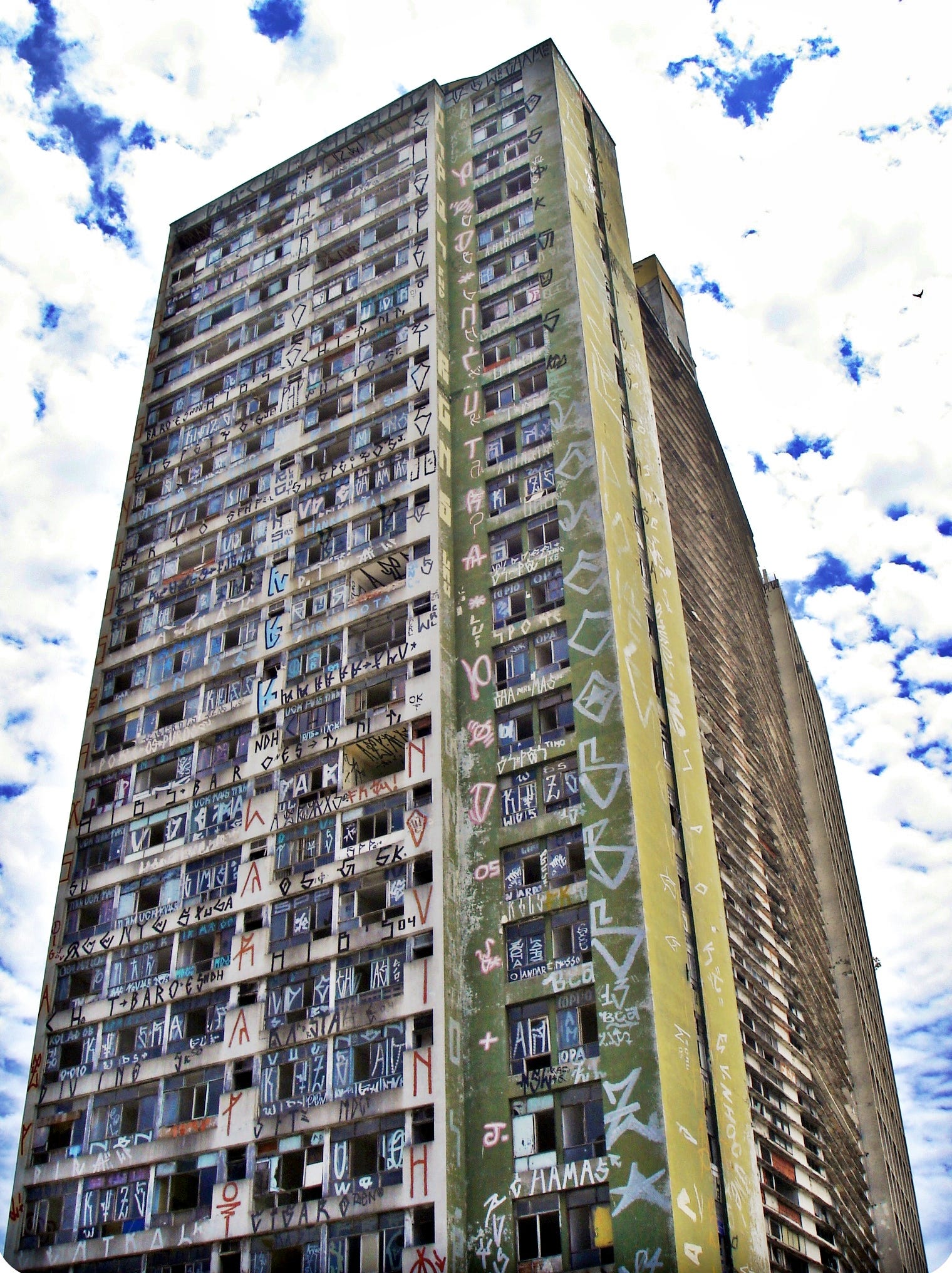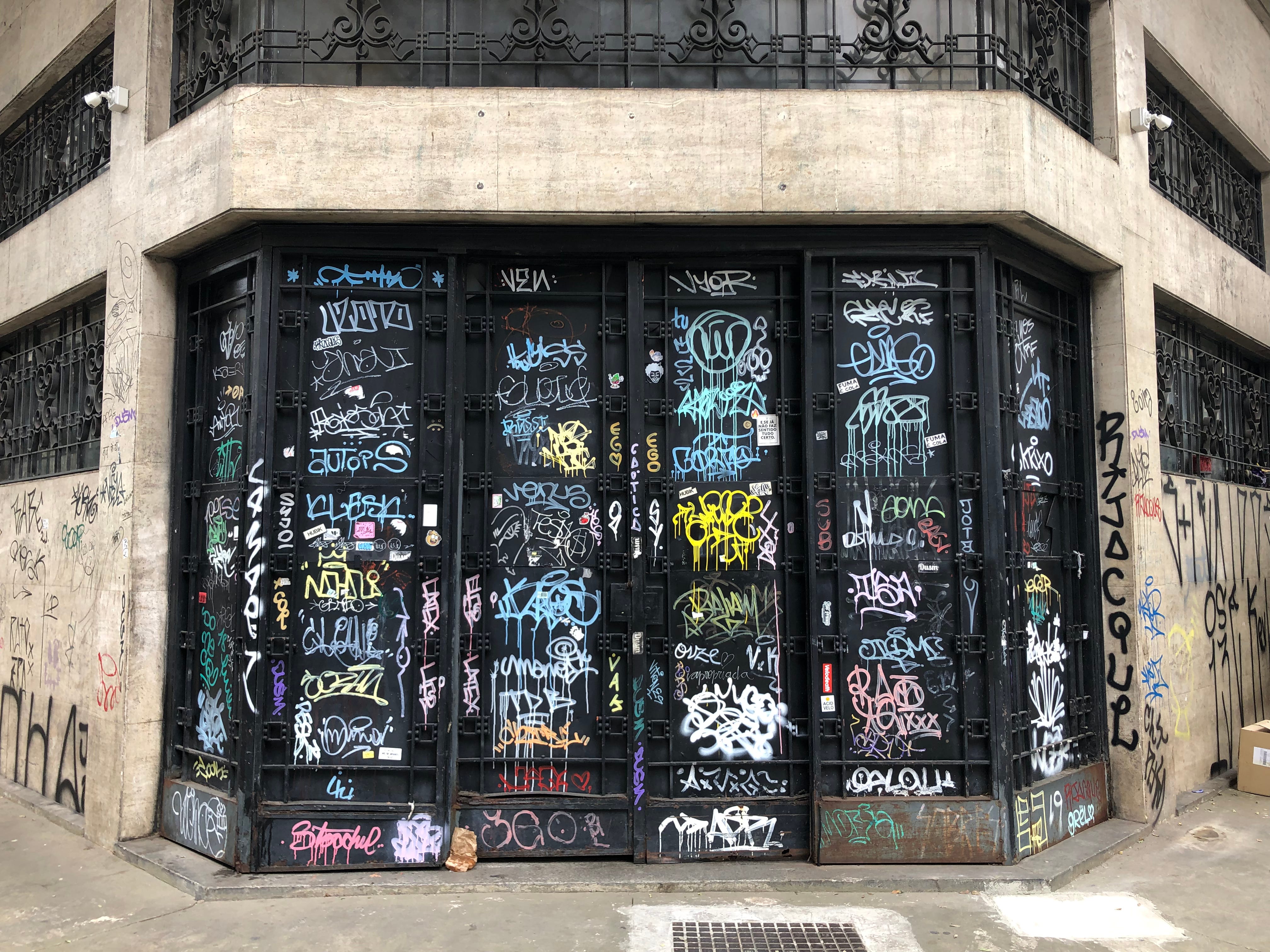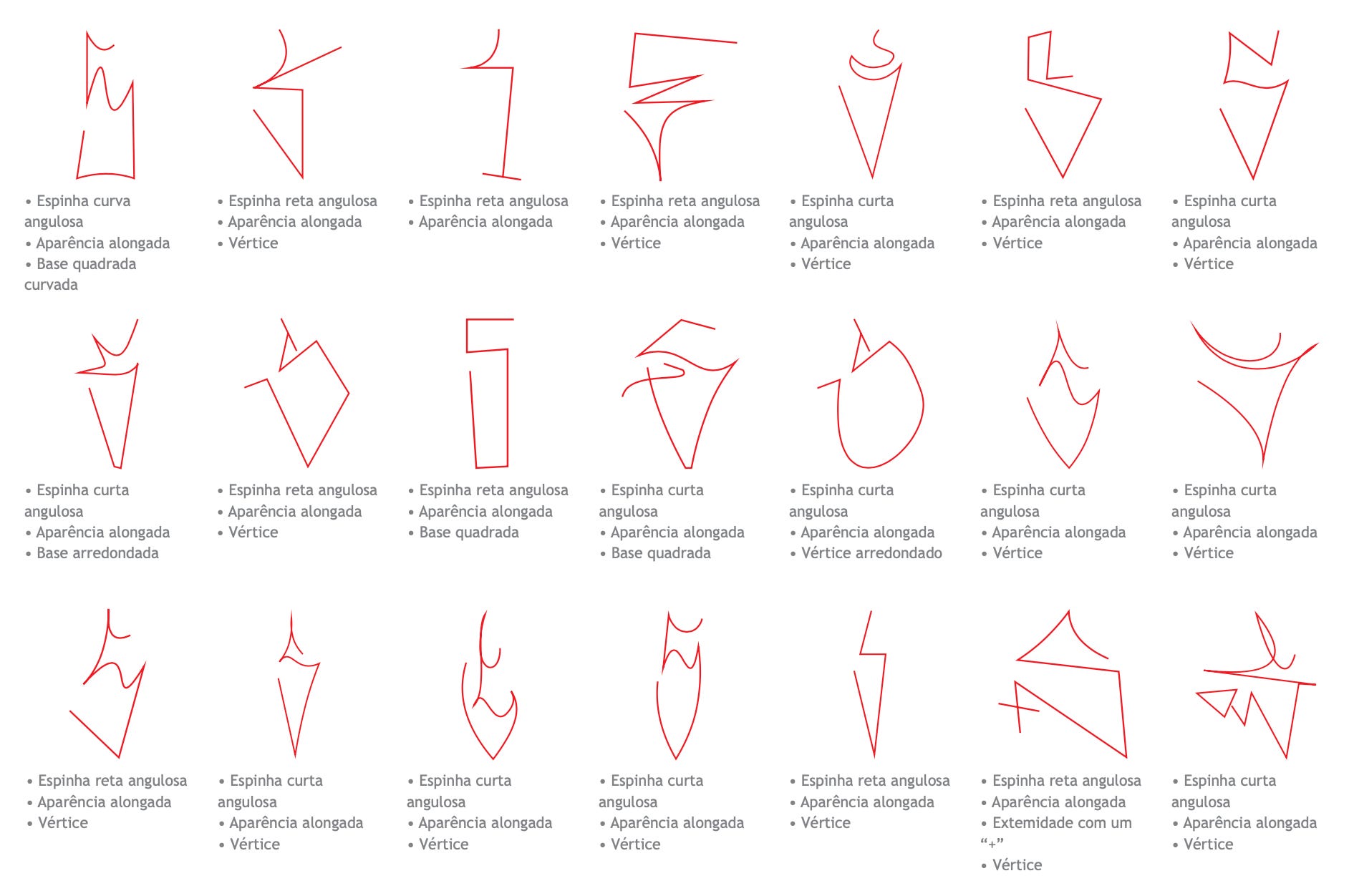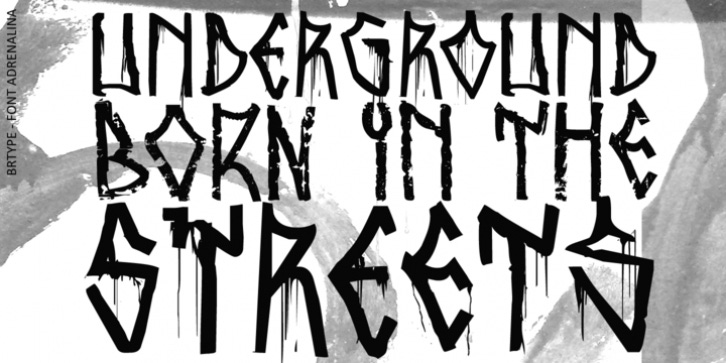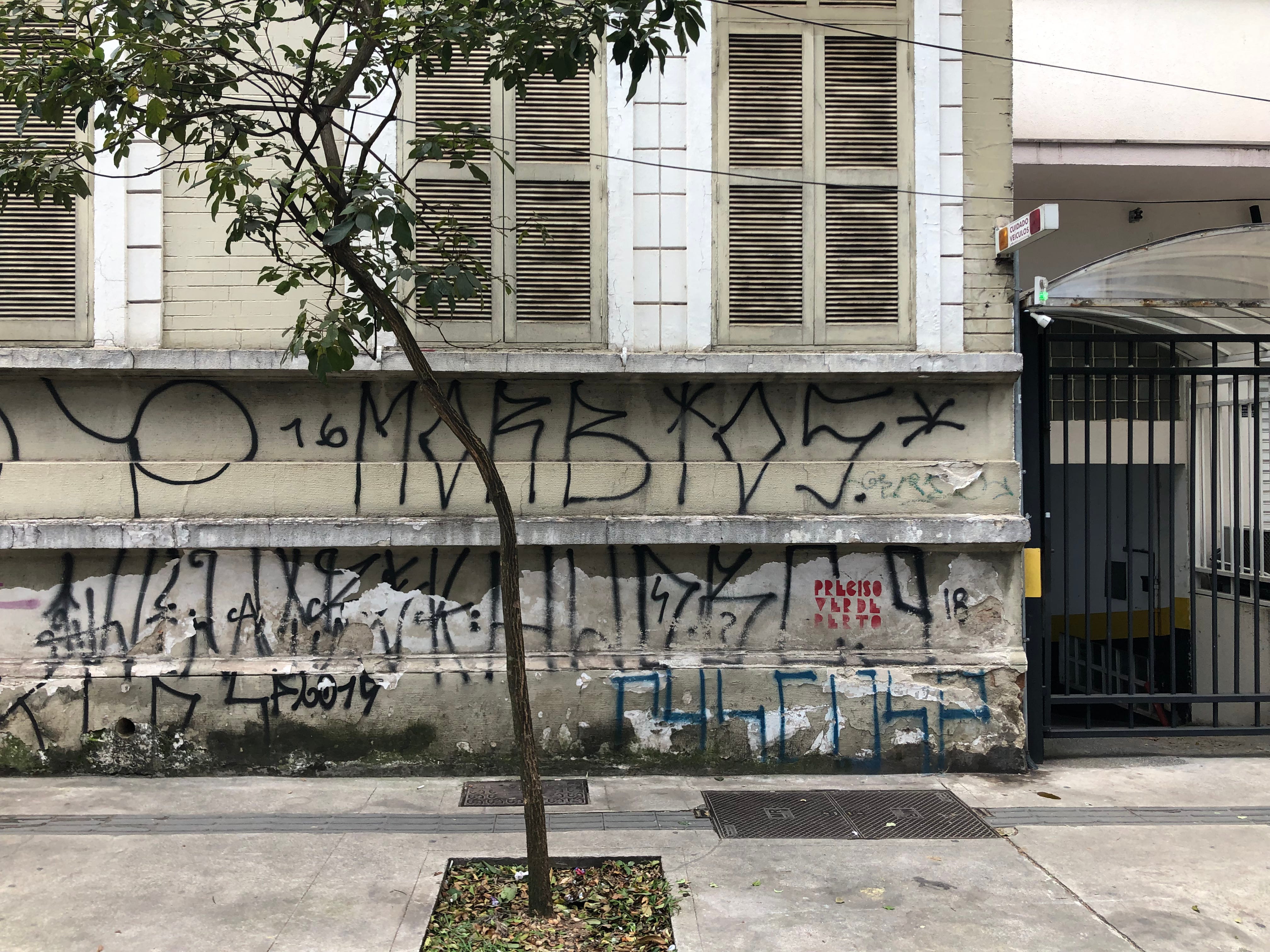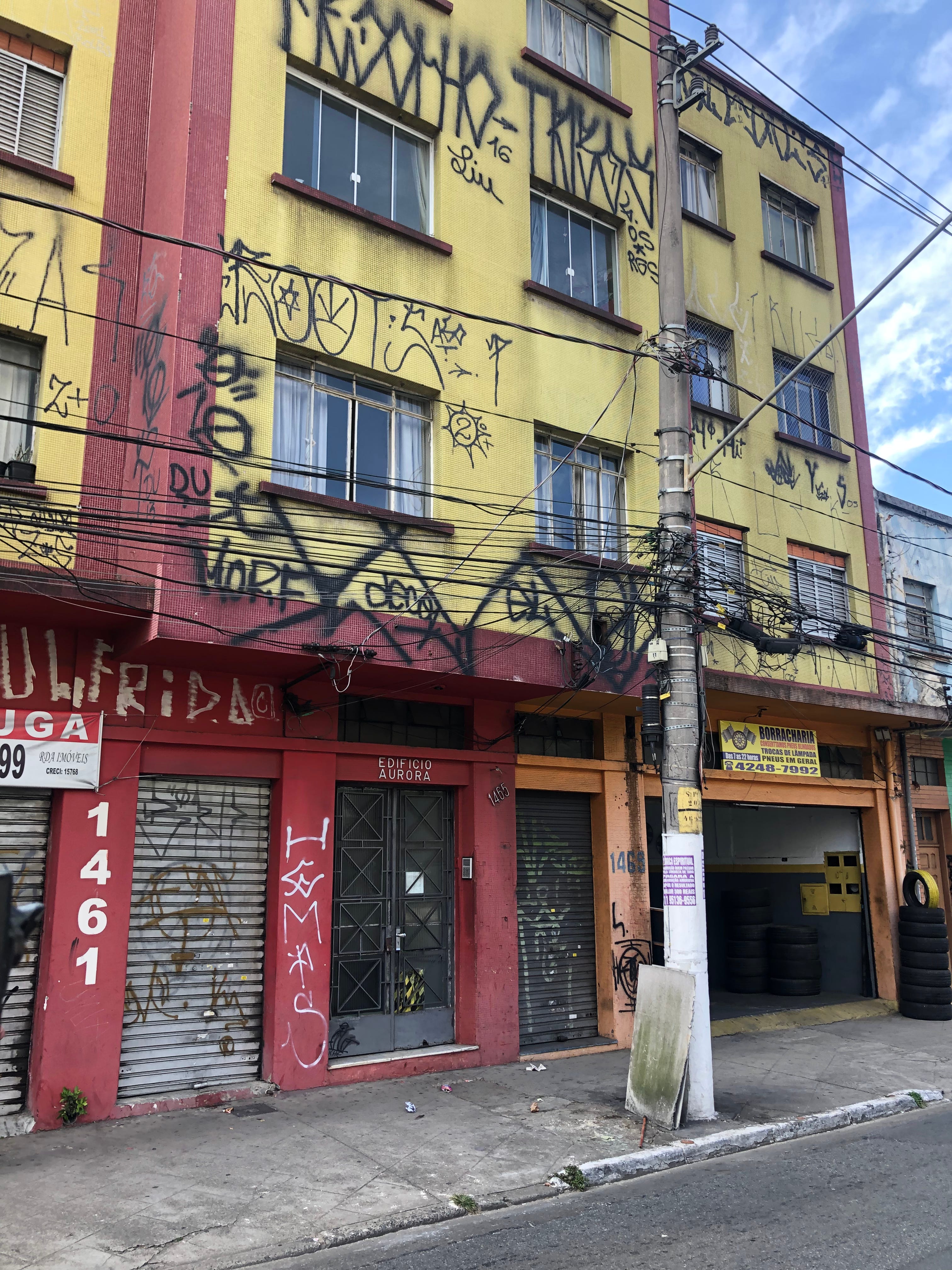
A paisagem urbana paulista constituída pelo Pixo
Existe uma convenção social que relaciona uma pessoa ao lugar que ela ocupa num dado contexto, baseado no status que ela possui. Essa convenção tende a colocar pessoas mais poderosas, dignas ou honradas num lugar mais alto, supostamente mais próximo de onde suas divindades estão e onde podem desempenhar com maior eficácia seu papel nas relações de poder dessa sociedade. Na São Paulo do começo do séc. XX, era comum dizer que “o dinheiro sobe o morro”, já que os pontos mais altos da cidade (como a Avenida Paulista) abrigavam os casarões das famílias comerciantes e industriais da capital paulista. Para baixo do morro, iam as fábricas, máquinas, a propriedade privada e os salários que permitiam aos trabalhadores o mínimo de sustento. Ao menos, era o que essas famílias pensavam.
Do alto do morro, também vinha uma relação de propriedade da cidade; a proximidade dessas famílias da elite paulistana com a política tornavam-nas praticamente donas da cidade, e ao seu gosto, a cidade foi dividida e zoneada marginalizando a população pobre (e preta, se considerarmos o pensamento higienista da época), tornando-a “invisível” para os seus. Vestígios dessa apropriação à força aparecem em muros, portões, nos altos de prédios e casarões, como um lembrete de que existe uma população “invisível” ali, mas que nunca vai hesitar em deixar sua marca e reclamar para si um espaço aos olhos de todo mundo, no amontoado de concreto da cidade. Assim como o Art Déco foi apropriado pela cidade, a pixação (com “x” mesmo, já explico isso) foi outro estilo de escrita que, logo quando chegou, ganhou uma cara própria; essa face avessa da moeda de São Paulo é o tema do Tipo Aquilo de hoje.
No início, era o spray, e o spray se fez pichação. Por enquanto, ainda com ch mesmo, como o dicionário manda. As primeiras latas de tinta em aerosol chegaram ao mercado nos anos 1950, dispensando o uso de pincel e outras ferramentas para pequenas pinturas. Em pouco tempo, virou um instrumento de protesto, permitindo no início que qualquer parisiense com muita coragem e pouca habilidade deixasse seu recado em muros e paredes, às vistas dos transeuntes. De Paris, o uso da tinta spray como protesto chegou a Nova Iorque e, enfim, ao Brasil, aparecendo inicialmente nos arredores de universidades, com mais foco nas mensagens contra a ditadura militar e a repressão no ambiente estudantil. A partir dos anos 1980, com a disseminação da cultura do hip-hop na capital paulista, também influenciada pelo punk, hard core e o metal, as letras em paredes tomam uma nova cara, com maior foco nas formas rápidas e incógnitas das letras.
A partir desse momento, o spray passa para a mão da massa, que subverte seu efeito contestador; antes o importante era que a mensagem fosse entendida por todos; depois, o negócio é estar à vista de todo mundo. Não que o pixador (a partir de agora, é com x) seja o Charada do universo de Gotham City… ele não tá nem aí se você não entende o que está escrito. Se ele quisesse que você entendesse, escreveria normalmente, como quando manda recado para a polícia, o poder público ou o amor da sua vida. A contestação não está mais na mensagem, mas sim na mera presença na paisagem urbana, indicando que aquele muro, monumento ou mesmo um prédio não pertence à pessoa que (supostamente) paga o IPTU e tem seu nome registrado na prefeitura. Até que seja pintado de novo, aquele lugar pertence ao pixador ou ao grupo que ele pertence, e só quem faz parte do rolê sabe quem é o rosto por trás daquela identidade visual cheia de símbolos feitos para caber em qualquer pedaço de muro. Não que a pixação tenha ficado menos política por isso.
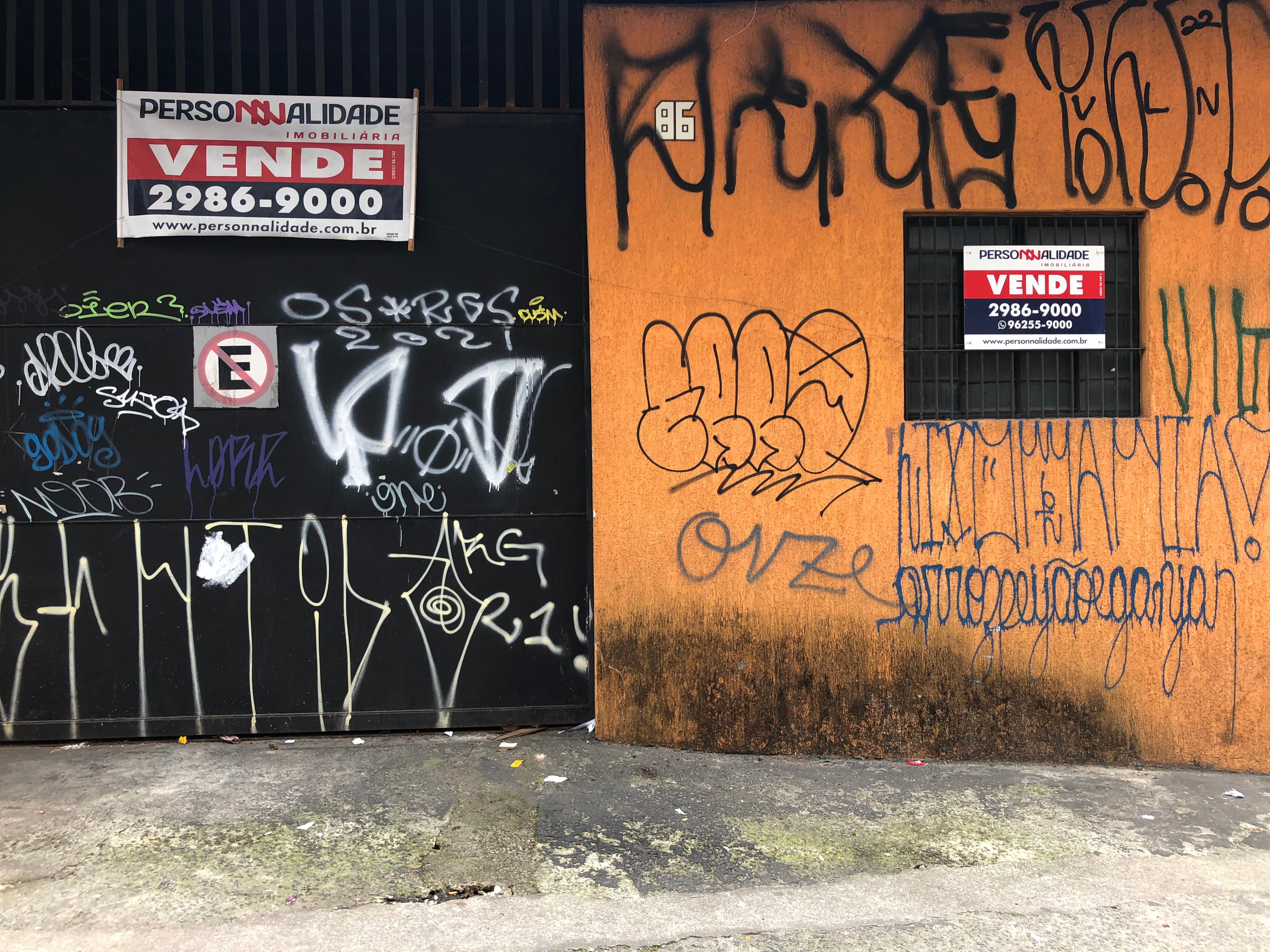
Isso não sou eu fazendo apologia ao pixo, pra que ele pareça mais rousseauniano na sua próxima discussão de boteco; é como os próprios pixadores vêm a sua criação. “É pra afrontar mesmo. É não estar nem aí mesmo […] é anarquia pura. É ódio”, como dito no documentário “Pixo” (2009). Aqui, por mais que a gente entenda o abismo da desigualdade social como um fator para que a pixação exista, isso é ingênuo; é só o começo de uma discussão que há décadas não tem resposta pronta. Então, vale a pena aqui ver o que há de tão paulista na pixação que, para o olhar mais atento, faz com que ela seja bem diferente de outros locais no Brasil… a começar pela verticalização da cidade. Com a proliferação de prédios e arranha-céus pelo espaço urbano, as letras pixadas tornam-se também verticais, pra ocupar todo espaço que possam, e uma pixação só é tida como bem-sucedida quando todas as letras tenham a mesma altura.
O punk e o metal foram pontes para que, inspirados pelas marcas de bandas como Iron Maiden, Kiss e Judas Priest, os pixadores paulistas trouxessem para suas marcas pessoais elementos da escrita rúnica, utilizada pelos povos germânicos pré-cristianização. O fotógrafo Adriano Choque trata desse fenômeno como um “presente” dos povos bárbaros da Europa medieval para os bárbaros da capital paulista. O aspecto “quebrado” das letras também lembra a passagem da caligrafia carolíngia para os primeiros modelos de alfabetos góticos, durante os séculos IX a XII, em que as formas retilíneas das letras, mais simples de reproduzir pelos copistas, tornaram-se predominantes no norte da Europa. No “pixo reto”, as letras com poucas curvas demandam menos habilidade manual, tornam-se mais facilmente reproduzidas, facilitam a escrita dela em quaisquer dimensões e viram uma característica que facilita a escrita tanto com spray quanto com pincel e rolo de tinta.
A propósito, os símbolos que você vê pixados nos muros não são um “alfabeto” ou um sistema de escrita exclusivo dos pixadores; são as 26 letras do nosso alfabeto latino, reinventadas a cada nova pixação e compartilhadas nos encontros das grifes, os grupos de pixadores. Cada grife vai lutar, muro por muro, pra ser a mais notória da região. No meio das letras, às vezes tem um símbolo em especial que identifica a grife, sua “marca” incontesta. A liberdade artística permite ao pixador reinventar cada letra a cada pixação; assim, uma documentação rigorosa dessas pixações mostra centenas de formas diferentes de escrever a mesma letra, misturando serifas, adornos e toda sorte de grafismos que valorizem-nas como obras de arte. É assim que os pixadores gostam de ser vistos, tendo sua arte como algo incômodo, que rebela-se contra o cânone artístico, e que a indústria cultural ainda não é capaz de digerir e devolver em algo palatável para a massa.
Colocar arte nessa discussão é mais um componente que faz do pixo algo que não tem uma conclusão, ou que alguma lei vai fazer com que desapareça da noite para o dia, como governo após governo tenta desde a década de 1980. O pixo é um fenômeno que acontece por vários motivos: tem o “ego” do pixador; tem a configuração urbana caótica de São Paulo que há muito tempo não se resume apenas em centro e subúrbio; tem os problemas decorrentes de desigualdade social e da marginalização de populações pobres; tem a necessidade de ser visto e reconhecido pelos seus pares, e outros fatores. Transformar o pixo numa arte mais aprazível para a população, em geral, por meio do grafitti e do street art, que os pixadores geralmente não atropelam, é o que a cidade consegue fazer para lidar com a existência dessa subcultura. O Beco do Batman, na Vila Madalena, é um símbolo de como São Paulo começa, de forma ainda bem pueril, a dialogar com o pixo. Outro exemplo de um passado não tão distante é a 29ª Bienal de Arte de São Paulo ter acomodado em um andar inteiro os pixadores que haviam invadido e pixado um andar vazio da edição anterior.
O pixo, além de ser crime ambiental no artigo 65 da Lei Federal nº 9.605, de 12 de fevereiro de 1998, com pena de prisão, variável de três meses a um ano, sob aplicação de multa, também é referência para type designers como Tony de Marco, Gustavo Lassala, e outros que publicaram fontes — gratuitas e pagas — com o intuito de reproduzir uma fração de sua estética transgressora no meio digital. Assim, a pixação — em especial, o pixo reto — torna-se cada vez mais entendida como uma expressão artística genuína e uma identidade visual de São Paulo, mesmo que, assim como as letras Art Déco, elas tenham vindo de fora do Brasil e moldadas conforme a necessidade e oportunidade do pixador de “ganhar a senha” de um prédio e espalhar sua assinatura em cada marquise, cada vez mais ao topo, onde o reconhecimento é mais valioso.
Embora este texto aborde apenas uma fração do que representa a subcultura do pixo em São Paulo, não quer dizer que ele resume-se a um estilo de escrita, ou uma mera atividade criminalmente reprimível. O pixo tem sua história, seus herois, suas lendas, artistas que ganharam projeção internacional, e desde o Cão Fila chegou para ficar e reivindicar seu espaço. Não importa se você estiver andando pela Avenida Paulista, pela 25 de Março, Berrini, Faria Lima, Santos Dumont ou Santo Amaro: em algum canto, o pixo reto estará lá, pra lembrar a quem quiser ler de que existe uma outra São Paulo dentro de São Paulo, que as pessoas comuns não querem saber ou lembrar que existe, em que para ser dono de um lugar e ter o respeito dos seus, basta ter coragem, vaidade e uma lata de tinta na mão.